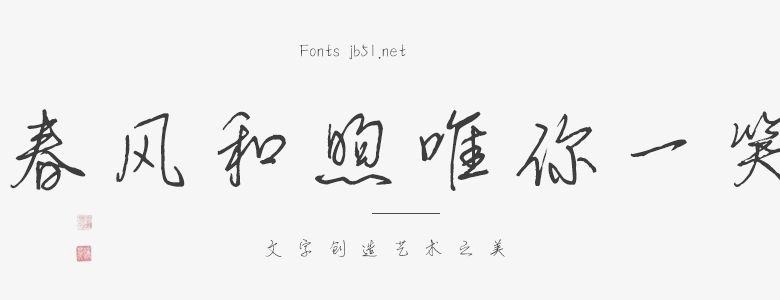
春風(fēng)和煦唯你一笑是一款極具藝術(shù)感和情感色彩的字體。這款字體的設(shè)計(jì)靈感來(lái)源于大自然的美好,以及人們對(duì)生活的熱愛(ài)和向往。 字體設(shè)計(jì)上,春風(fēng)和煦唯你一笑采用了流暢的線條和柔和的曲線,使得每個(gè)字母都顯得溫暖而親切。字體的曲線處理非常精致,呈現(xiàn)出一種春風(fēng)拂面的感覺(jué),讓人感受到生活中的美好和溫馨。 在字體的細(xì)節(jié)處理上,春風(fēng)和煦唯你一笑的筆畫較細(xì),但是非常清晰,沒(méi)有任何模糊或含糊不清的地方。字體的字母間距較為寬松,使得文字整體看起來(lái)非常舒適,不會(huì)感到擁擠或壓抑。此外,字體中還融入了一些細(xì)節(jié)設(shè)計(jì),比如在字母“o”的地方設(shè)計(jì)成了一個(gè)笑臉,寓意著“笑對(duì)人生,溫暖如春”。 總體來(lái)說(shuō),春風(fēng)和煦唯你一笑是一款非常優(yōu)美、溫暖、親切的字體,適合用于各種場(chǎng)合,無(wú)論是書籍的排版、廣告的文字設(shè)計(jì)、還是網(wǎng)站的標(biāo)題等,都能讓讀者感受到一種溫馨和親切的感覺(jué),給人帶來(lái)愉悅和舒適的閱讀體驗(yàn)。